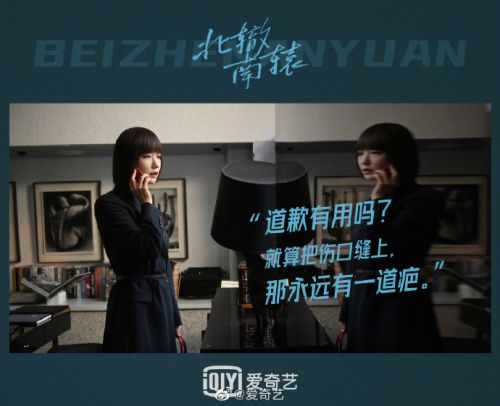
字体圈欣意冠黑体
字体圈欣意冠黑体是一款风格鲜明的创意字体,以“尖锐”为核心设计语言,兼具实用性与视觉张力,是免费商用领域中极具辨识度的选择。 字体整体字形方正,重心居中且中宫适中,结构稳定的同时,为笔画设计预留了充足的创意空间。笔型以利落直角为主,线条刚劲有力,部分笔画末端添加简洁装饰元素,既强化了“尖锐”的风格特质,又避免了过度繁复,呈现出干练而精致的视觉效果。 字体笔画较粗且粗细均匀,方头设计搭配笔画间的断开连接,让每个字符在保持硬朗气质的同时,减少了视觉拥堵感,阅读清晰且富有节奏感。作为免费商用字体,字体圈欣意冠黑体适用于海报标题、品牌LOGO、广告宣传等多种场景,无论是需要突出个性的创意项目,还是追求醒目效果的商业设计,都能凭借其独特的风格助力作品脱颖而出。